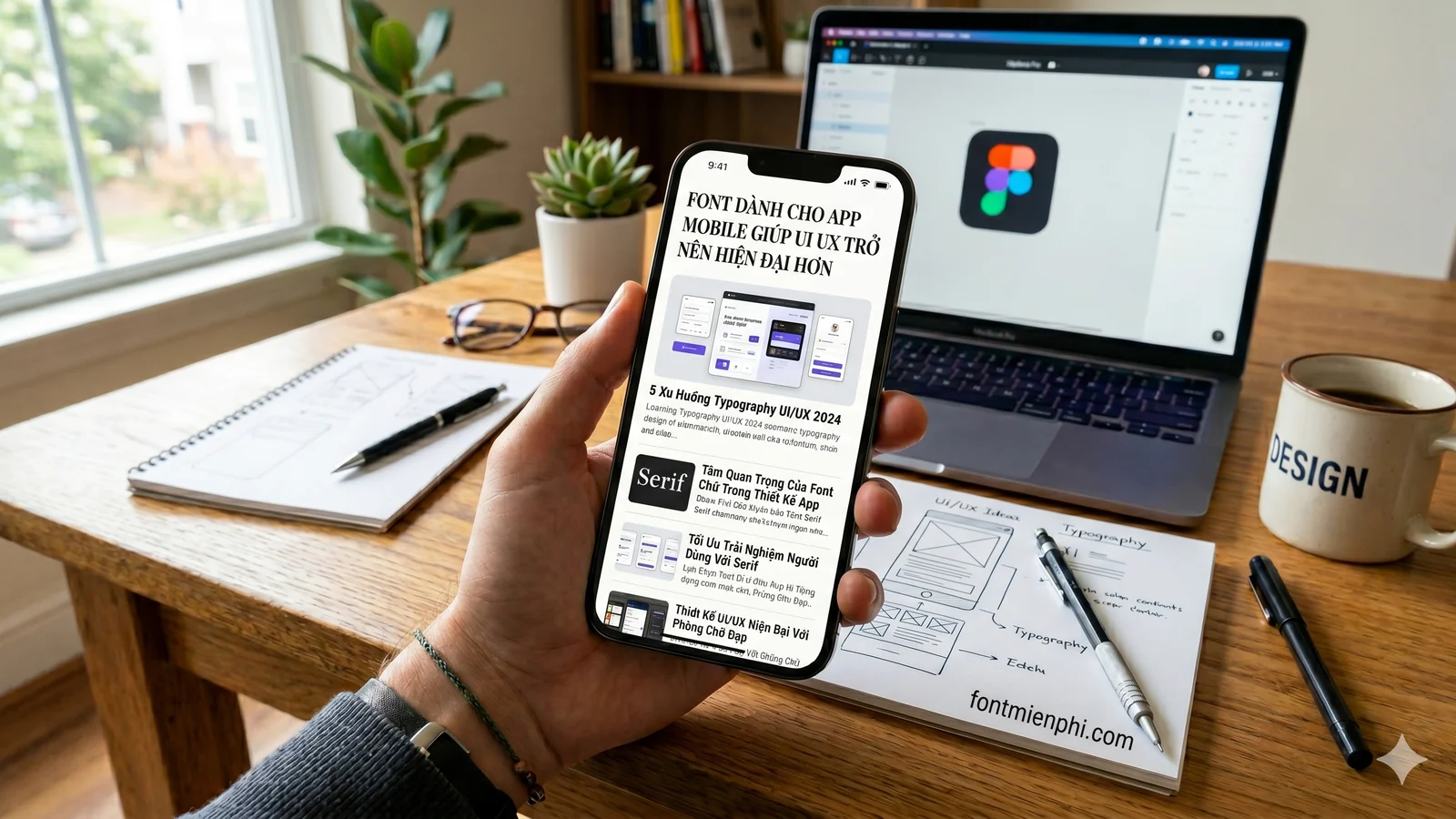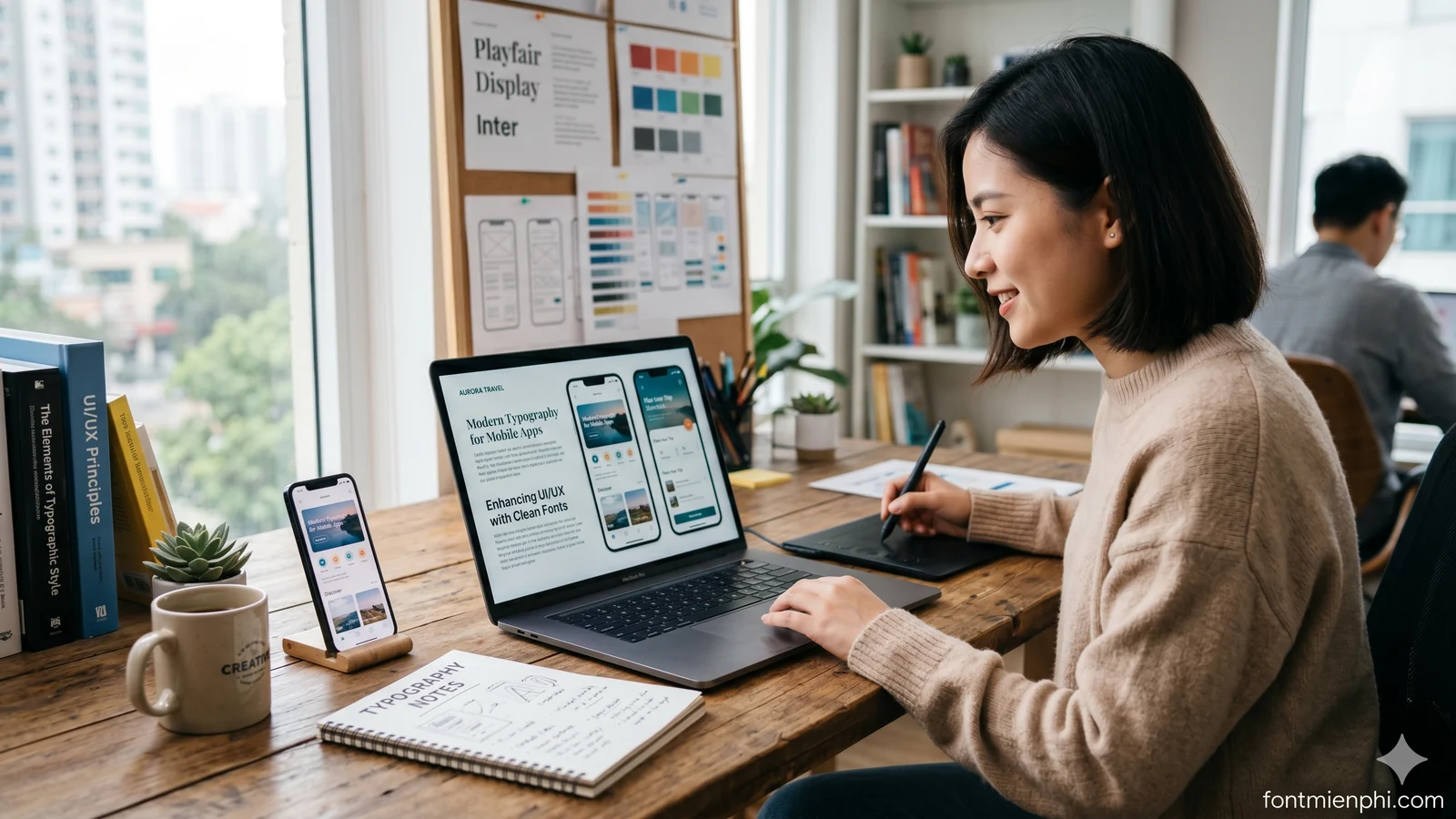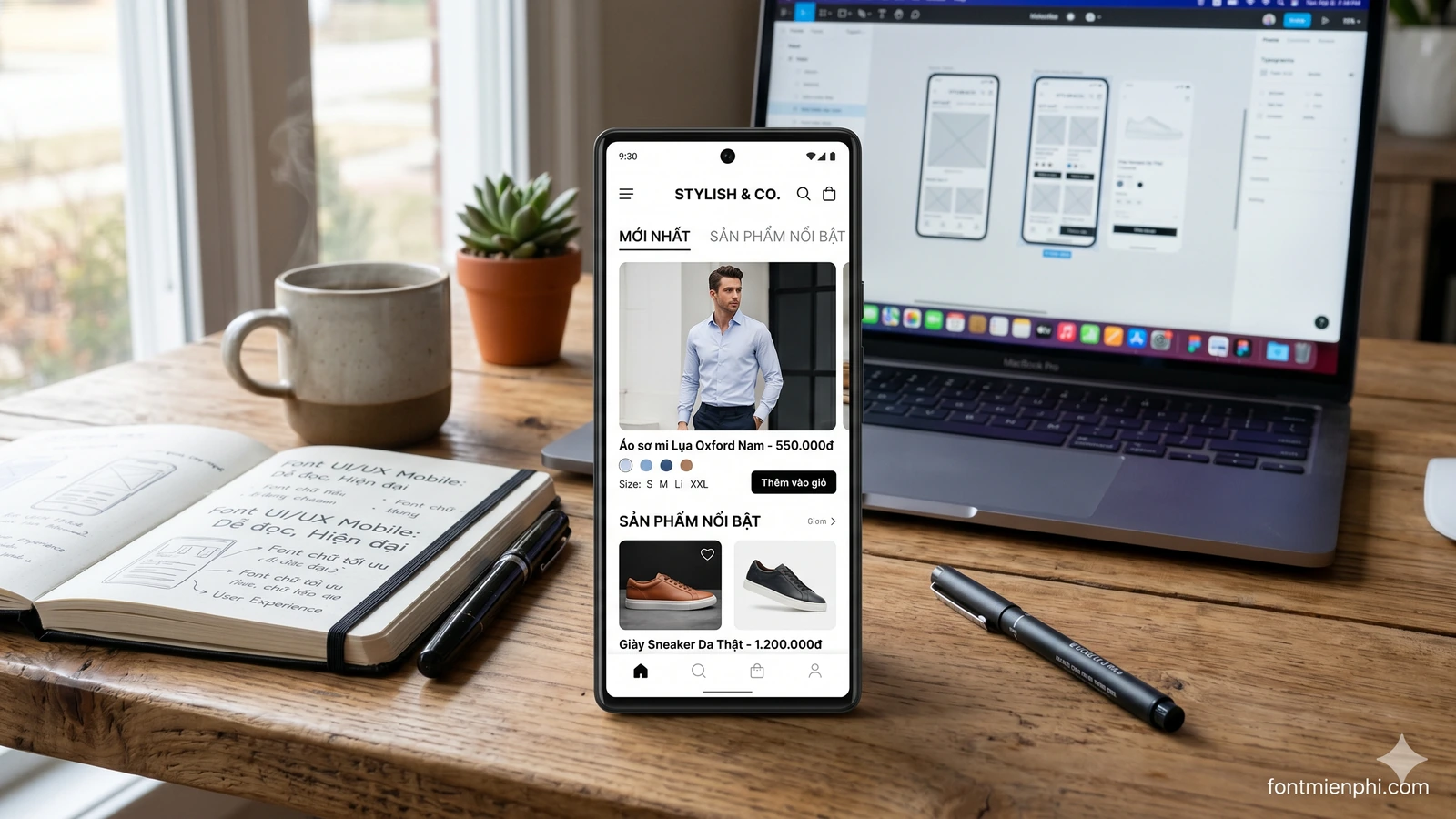
Font Dành Cho App Mobile Giúp UI UX Trở Nên Hiện Đại Hơn
Bài viết này phân tích tầm quan trọng của kiểu chữ trong thiết kế giao diện và trải nghiệm người dùng trên ứng dụng di động. Chúng tôi giới thiệu các bộ phông chữ hiện đại dẫn đầu xu hướng, đồng thời cung cấp hướng dẫn chi tiết giúp tối ưu hóa khả năng đọc, nâng tầm thẩm mỹ và tạo dấu ấn riêng cho sản phẩm công nghệ của bạn.
Font Dành Cho App Mobile Giúp UI UX Trở Nên Hiện Đại Hơn - anh 1
Tầm Quan Trọng Của Typography Trong Thiết Kế Giao Diện Và Trải Nghiệm Người Dùng
Trong thế giới công nghệ số ngày nay, một ứng dụng di động không chỉ cần hoạt động trơn tru mà còn phải sở hữu một diện mạo bắt mắt và mang lại trải nghiệm người dùng tối ưu. Khi nói đến giao diện người dùng và trải nghiệm người dùng, nhiều người thường nghĩ ngay đến màu sắc, hình ảnh, hoặc các hiệu ứng chuyển động. Tuy nhiên, có một yếu tố tĩnh lặng nhưng lại đóng vai trò quyết định đến sự thành bại của một ứng dụng, đó chính là nghệ thuật xếp chữ.
Kiểu chữ không chỉ đơn thuần là công cụ để hiển thị văn bản. Nó là tiếng nói của thương hiệu, là người dẫn đường cho ánh mắt của người dùng, và là nền tảng của mọi giao tiếp trên môi trường kỹ thuật số. Trên một màn hình điện thoại di động có kích thước hạn chế, nơi không gian dành cho thiết kế vô cùng khiêm tốn, văn bản thường chiếm phần lớn diện tích hiển thị. Việc lựa chọn sai kiểu chữ có thể dẫn đến hậu quả nghiêm trọng, khiến người dùng cảm thấy mỏi mắt, khó nắm bắt thông tin và cuối cùng là từ bỏ ứng dụng của bạn. Ngược lại, một kiểu chữ phù hợp sẽ làm cho toàn bộ giao diện trở nên gọn gàng, hiện đại và thân thiện hơn rất nhiều.
Về mặt tâm lý học, mỗi bộ chữ mang một cảm xúc và tính cách riêng. Các đường nét bo tròn thường tạo ra cảm giác gần gũi, vui vẻ và thân thiện, rất phù hợp cho các ứng dụng giải trí hoặc giáo dục dành cho trẻ em. Những đường nét cứng cáp, góc cạnh lại toát lên vẻ chuyên nghiệp, đáng tin cậy và mạnh mẽ, thường được ưa chuộng trong các ứng dụng tài chính, ngân hàng hoặc tin tức. Do đó, việc am hiểu về nghệ thuật xếp chữ không chỉ giúp nhà thiết kế tạo ra những giao diện đẹp mắt mà còn giúp họ truyền tải đúng thông điệp và giá trị cốt lõi của thương hiệu đến với người dùng.
Hơn thế nữa, một hệ thống phân cấp kiểu chữ tốt sẽ trực tiếp cải thiện trải nghiệm người dùng bằng cách hướng dẫn họ cách đọc và tương tác với ứng dụng. Bằng cách sử dụng các kích thước và sắc thái khác nhau của cùng một kiểu chữ, nhà thiết kế có thể dễ dàng phân biệt đâu là tiêu đề chính, đâu là phụ đề, và đâu là nội dung chi tiết. Sự rõ ràng này giúp giảm thiểu tối đa gánh nặng nhận thức cho người dùng, cho phép họ tìm kiếm thông tin và hoàn thành các tác vụ một cách nhanh chóng và hiệu quả nhất.
Những Tiêu Chí Cốt Lõi Khi Lựa Chọn Font Chữ Cho App Mobile
Việc quyết định sử dụng bộ chữ nào cho ứng dụng di động không nên dựa vào cảm tính cá nhân hay xu hướng nhất thời. Nó đòi hỏi một quá trình đánh giá cẩn thận dựa trên nhiều tiêu chí kỹ thuật và thẩm mỹ khác nhau. Dưới đây là những yếu tố quan trọng nhất mà mọi nhà thiết kế giao diện cần phải xem xét kỹ lưỡng.
Khả năng đọc lướt và tính rõ ràng: Khả năng đọc lướt chỉ mức độ dễ dàng mà mắt người có thể phân biệt các ký tự riêng lẻ với nhau. Trên màn hình di động, đặc biệt là khi di chuyển hoặc dưới điều kiện ánh sáng kém, tính rõ ràng là yếu tố sống còn. Bạn cần kiểm tra xem các ký tự như chữ l viết thường, chữ I viết hoa và số 1 có dễ bị nhầm lẫn hay không. Tương tự, các chữ cái như c, e và o cũng cần có thiết kế đủ mở để người dùng không phải căng mắt khi phân biệt chúng ở kích thước nhỏ.
Chiều cao của chữ x: Đây là tỷ lệ chiều cao của các chữ cái viết thường so với chữ cái viết hoa trong cùng một bộ chữ. Những bộ chữ có chiều cao chữ x lớn thường có không gian bên trong các vòng lặp rộng hơn, giúp chúng dễ đọc hơn hẳn ở các định dạng kích thước bé. Tuy nhiên, nếu chiều cao này quá lớn, sự khác biệt giữa chữ viết hoa và viết thường sẽ bị xóa nhòa, làm mất đi sự nhịp nhàng tự nhiên của dòng văn bản. Do đó, một tỷ lệ cân đối mang tính hình học chuẩn xác là điều vô cùng cần thiết để đảm bảo cả tính thẩm mỹ và khả năng hiển thị.
Sự đa dạng về độ đậm nhạt: Một bộ chữ lý tưởng cho ứng dụng di động ngày nay phải bao gồm nhiều mức độ đậm nhạt khác nhau, từ cực mảnh đến cực đậm. Sự đa dạng về trọng lượng chữ này cho phép bạn tạo ra một hệ thống phân cấp thông tin rõ ràng, rành mạch mà không cần phải thay đổi kiểu chữ liên tục. Nó giúp duy trì sự đồng nhất, tính nguyên bản trong thiết kế tổng thể, trong khi vẫn đảm bảo tính linh hoạt tối đa để nhấn mạnh các yếu tố giao diện quan trọng.
Tính đa ngôn ngữ và hỗ trợ ký tự bản địa: Nếu ứng dụng của bạn hướng tới người dùng toàn cầu hoặc hoạt động tại các quốc gia sử dụng các ngôn ngữ có dấu câu phức tạp như tiếng Việt, việc hỗ trợ đa ngôn ngữ là một tiêu chí mang tính bắt buộc. Một bộ chữ dù có thiết kế đẹp đến mấy nhưng lại bị lỗi phông, thiếu ký tự hoặc hiển thị dấu câu không hợp lý, xộc xệch cũng sẽ phá hỏng hoàn toàn trải nghiệm người dùng, đồng thời làm giảm đi sự uy tín và chuyên nghiệp của toàn bộ hệ thống ứng dụng.
Khả năng co giãn và hiển thị mượt mà trên các độ phân giải khác nhau: Các thiết bị di động hiện nay rất đa dạng về kích thước vật lý và mật độ điểm ảnh. Từ những chiếc điện thoại thông minh giá rẻ với màn hình độ phân giải thấp, đến những chiếc máy tính bảng cao cấp với màn hình siêu nét. Bộ chữ bạn chọn cần phải được tối ưu hóa kỹ thuật đồ họa thật tốt để có thể hiển thị sắc nét trên mọi loại màn hình mà không bị mờ nhòe, gãy nét hay mất đi các chi tiết thiết kế đặc trưng.
Hoàn toàn bỏ qua việc tối ưu cho các yếu tố ngôn ngữ đặc thù bản địa: Một sai lầm cực kỳ nghiêm trọng mà rất nhiều nhà thiết kế thường mắc phải là chỉ kiểm tra thiết kế bố cục giao diện bằng các đoạn văn bản mẫu sử dụng tiếng Anh. Tuy nhiên, khi ứng dụng thực tế được dịch và chuyển sang hiển thị bằng các ngôn ngữ khác, các vấn đề nghiêm trọng mới bắt đầu lộ diện. Chẳng hạn như tiếng Đức luôn nổi tiếng với những từ ghép có độ dài cực kỳ khủng khiếp, hoặc tiếng Việt với một hệ thống dấu thanh điệu phức tạp nằm chồng lên trên và dưới các chữ cái, khi đó bố cục giao diện ban đầu có thể bị phá vỡ hoàn toàn và trở nên méo mó. Việc không tính toán và chừa đủ không gian theo chiều dọc cho chiều cao của các lớp dấu thanh, hoặc không xây dựng một cơ chế tự động xuống dòng hợp lý, an toàn cho những từ có độ dài bất thường, sẽ ngay lập tức khiến cho văn bản bị lỗi đè lên nhau chồng chéo, các nút bấm bị đẩy ra ngoài màn hình, gây mất chữ và làm suy giảm vô cùng nghiêm trọng chất lượng đồ họa cũng như độ tin cậy của ứng dụng.